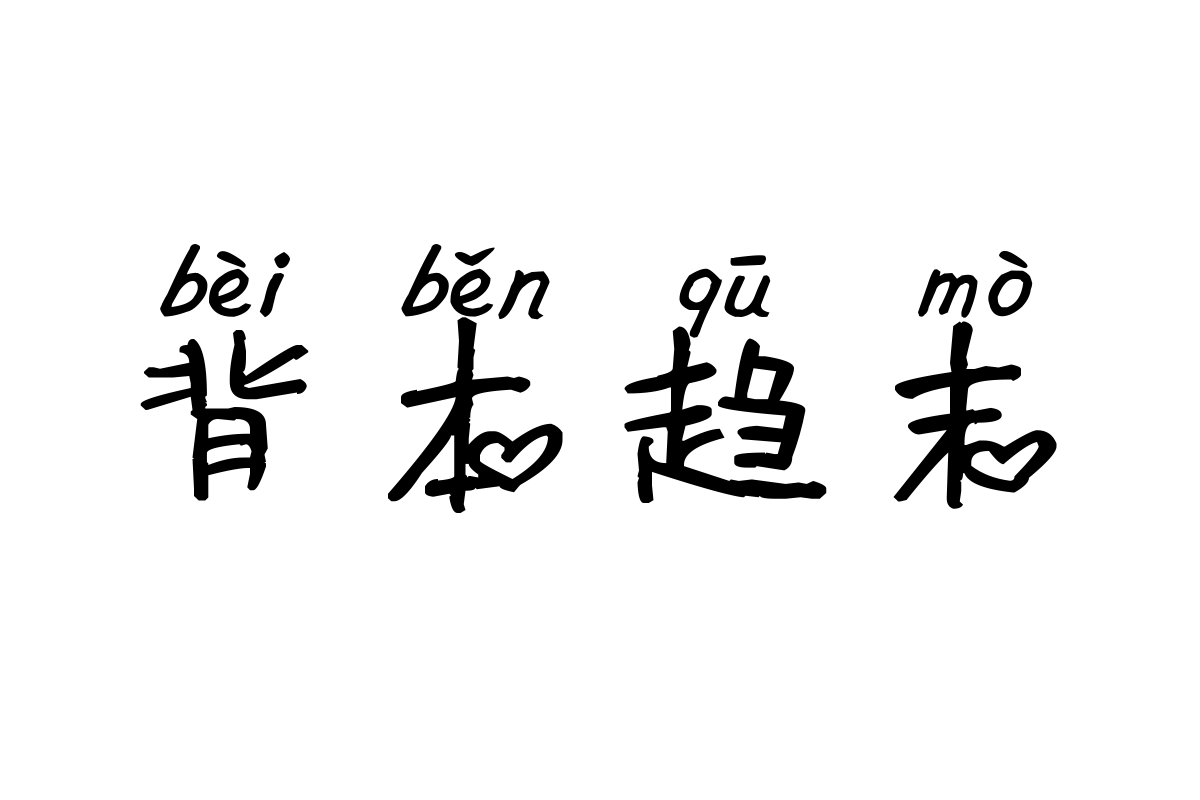
米开爱情的魔咒拼音体是一款中文字体,由设计师米开设计。这款字体以“爱情”为主题,将“魔咒”元素融入其中,创造出独特的视觉效果。它的字形独特,线条流畅,给人一种神秘、浪漫的感觉。
这款字体适用于各种文字排版,如广告、海报、书籍、网页等。它不仅能够吸引人们的目光,还能够传达出一种浪漫、唯美的氛围。因此,这款字体在设计领域受到了广泛的欢迎和喜爱。